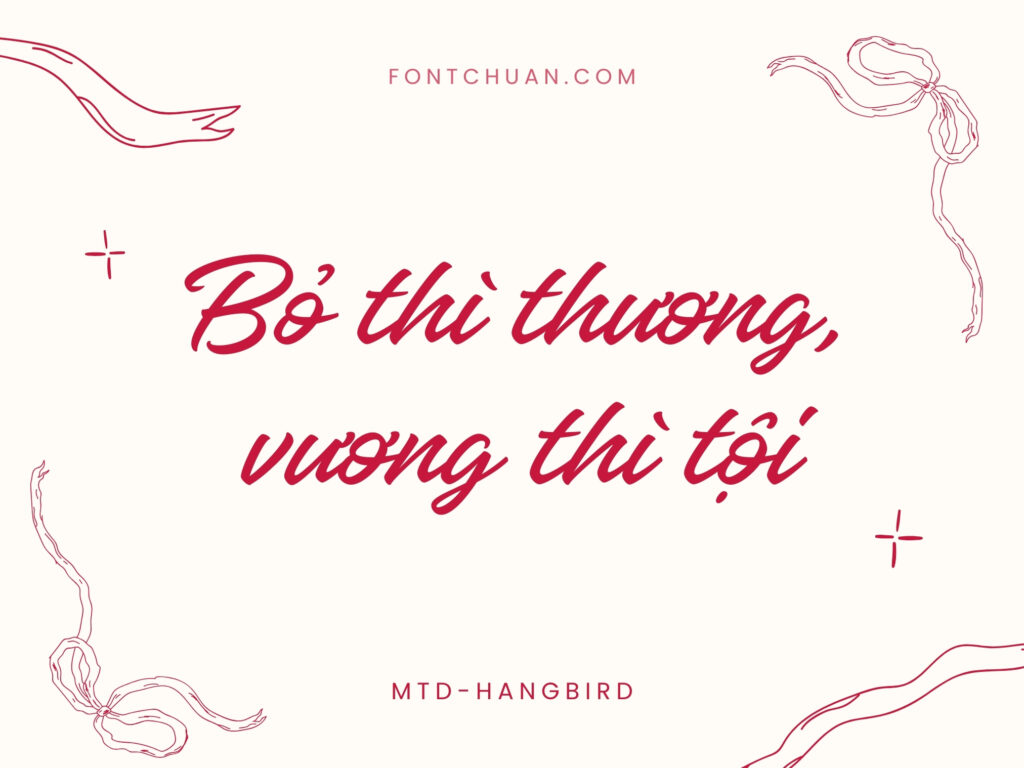
Font MTD Hangbird Việt Hóa
Tác giả Font: Mika Melvas
Font MTD Hangbird là một kiểu chữ viết tay hiện đại với phong cách mềm mại và thân thiện, được thiết kế bởi Mika Melvas và Việt hóa bởi Mộc Hạ. Font hỗ trợ tiếng Việt cùng hơn 90 ngôn ngữ khác, đáp ứng tốt nhu cầu sử dụng đa dạng trong các thiết kế đa quốc gia. Đây là một phông chữ được thành viên của Font Chuẩn chọn lọc, sưu tầm và ứng dụng thực tế vào nhiều dự án thiết kế thương hiệu, truyền thông và thiệp mời với hiệu quả cao về mặt thẩm mỹ.
MTD Hangbird gây ấn tượng với các nét bút tay uốn lượn tự nhiên, kết hợp giữa sự tinh tế và độ dễ đọc, rất phù hợp để sử dụng trong các thiết kế mang yếu tố cá nhân hóa như logo, chữ ký thương hiệu, tiêu đề, bìa tạp chí, thiệp cưới và bao bì mỹ phẩm. Phông chữ này đặc biệt lý tưởng cho các ngành quảng cáo, giáo dục, công nghệ, thiệp cưới và ảnh cưới. Bên cạnh đó, font còn được ưa chuộng trong các dịp như Tết, Giáng sinh, Valentine hay lễ hội yêu cầu nét mềm mại và lãng mạn trong thiết kế.